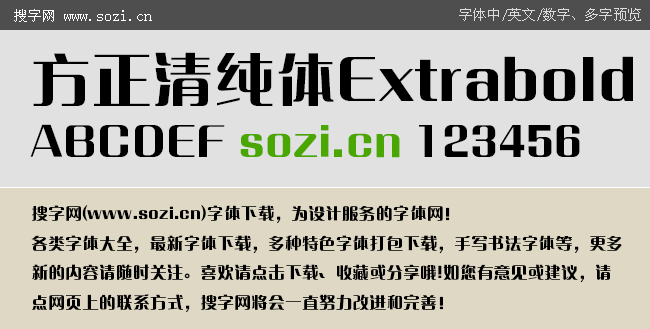
方正清純體Extrabold
搜字網(wǎng)提供一款方正清純體Extrabold中文藝術(shù)字體下載,方正清純體筆畫(huà)粗細(xì)對(duì)比明顯,橫細(xì)豎粗,筆形富于變化,整體給人清新、靈動(dòng)、優(yōu)美、圓潤(rùn)之感,適合應(yīng)用于廣告設(shè)計(jì)、名片設(shè)計(jì)、包裝印刷、兒童產(chǎn)品設(shè)計(jì)等應(yīng)用。
- 風(fēng)格類(lèi)別: 現(xiàn)代藝術(shù)體